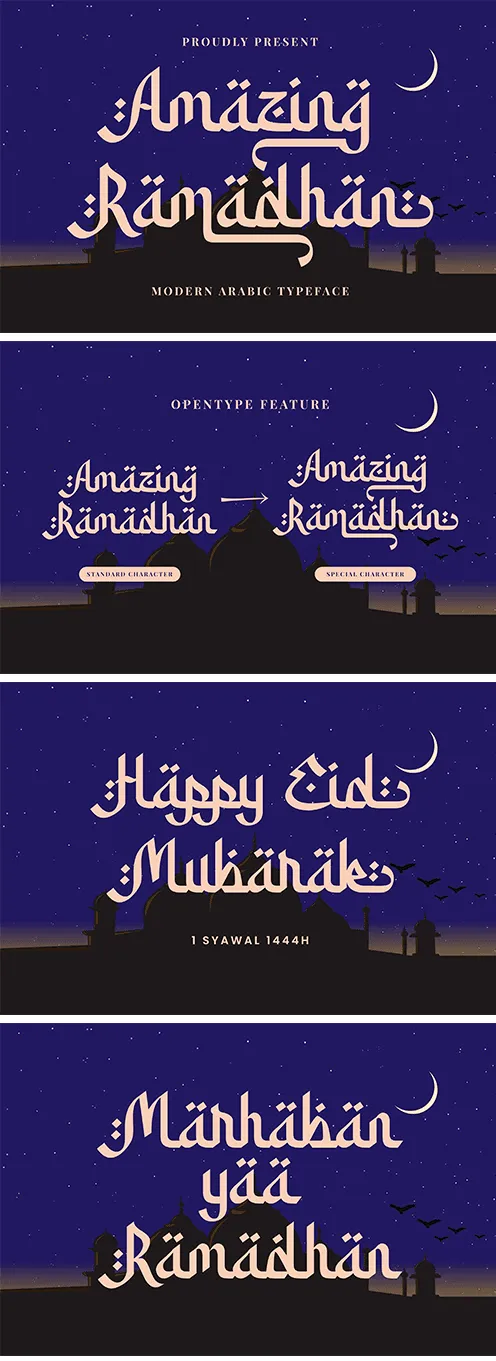
رمضان المذهل – الخط العربي الحديث
Amazing Ramadhan – Modern Arabic Typeface
رمضان المذهل هو خط عربي مذهل ذو طابع أصيل وغير رسمي. يجعل أسلوبه الطبيعي والفريد من نوعه مناسبًا بشكل لا يصدق لمجموعة كبيرة من التصاميم. الحد الوحيد هو خيالك!
هذا الخط مشفر بواسطة PUA مما يعني أنه يمكنك الوصول إلى جميع الحروف الرسومية والأربطة المذهلة بسهولة!